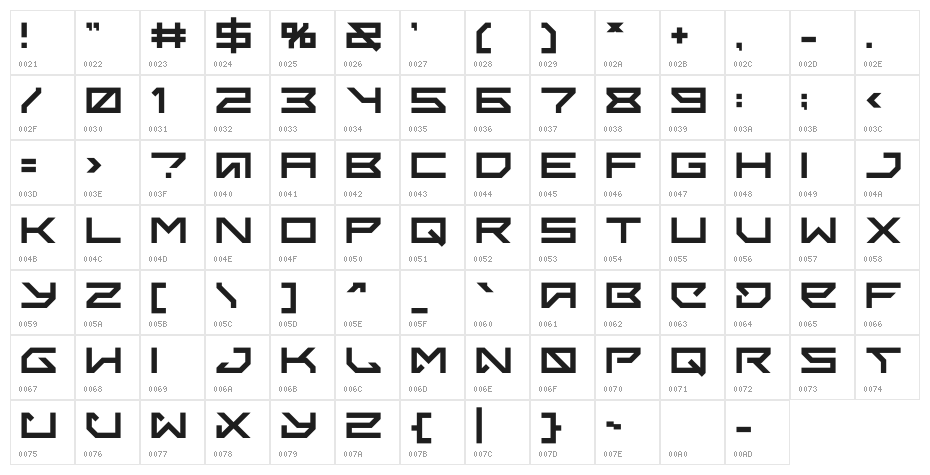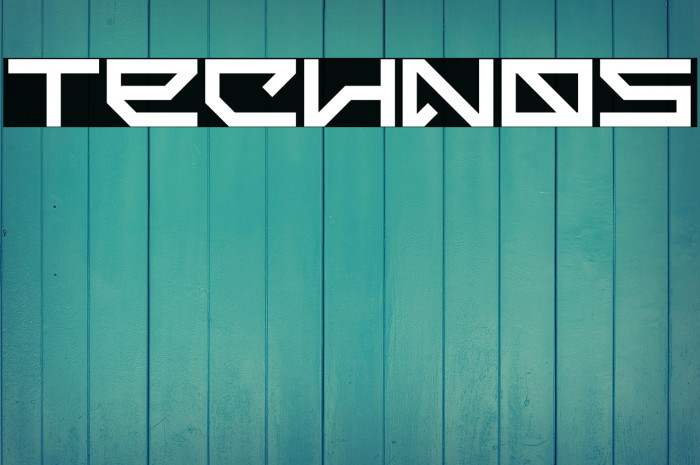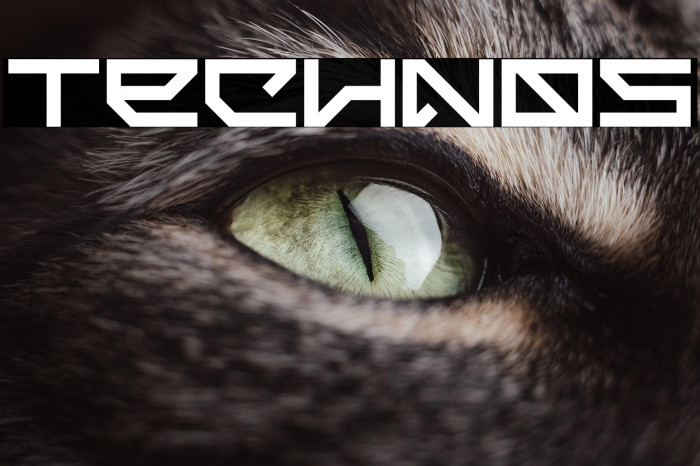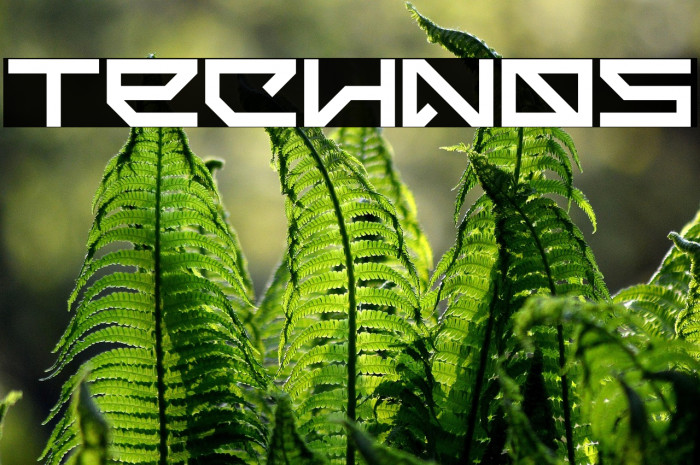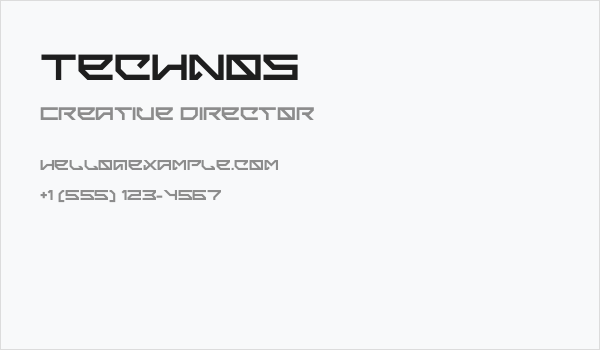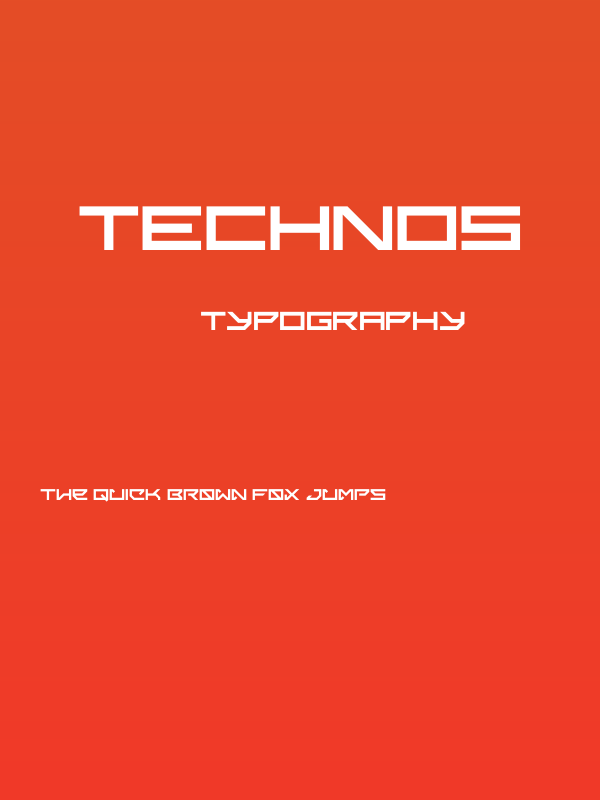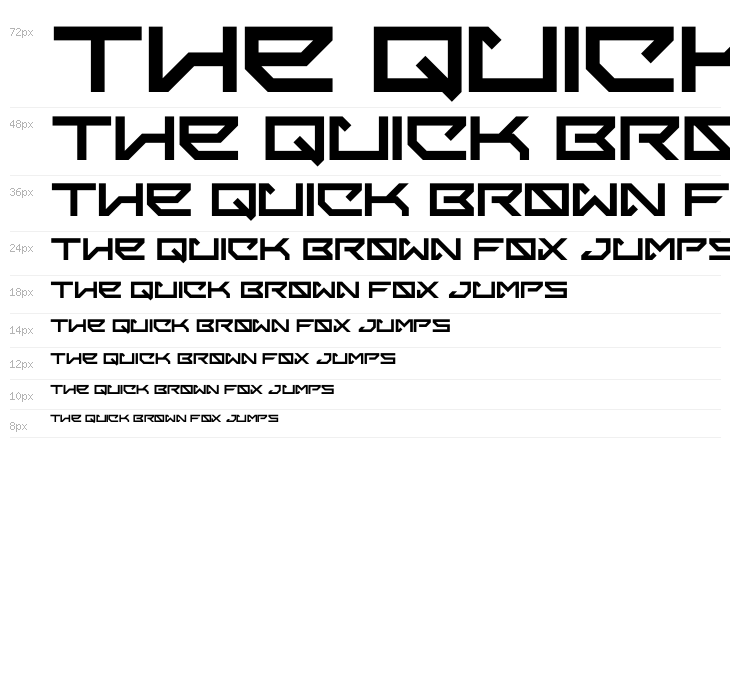
Technos Font
Fonts by Figuree Studio
| Vorgeschlagene Projekte | Ideal for technology branding, sci-fi movie posters, video game titles, and modern advertising campaigns. |